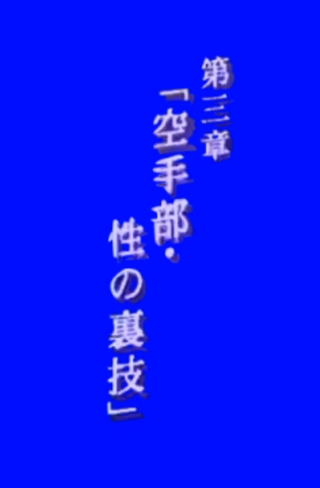
インタビュー テロップ フォント
インタビュー テロップ フォント. そしてこのフォントは 最初に全て決めておきましょう テロップを入れるたびにフォント何にしようかな〜と選ぶ時間がもったいないです 時間短縮のためにもフォントを決めておく事をオススメします 状況に応じたおすすめのフリーフォントを一部紹介し. 3 受注時に要確認 テロップは作業時間が数倍に 31 webではテロップが必須な時代;. 4 見やすいテロップとは 41 文字の色や輪郭は明度差を意識する;.
字幕とテロップはどう違うのですか。 テロップは一般的にはテレビ画面に映し出された文字のことを指しますが、当社では便宜上、字幕作成とテロップ作成を以下のように区別しています。 srtやvttファイル作成のみお願いできますか。 はい、可能です。. 3 受注時に要確認 テロップは作業時間が数倍に 31 webではテロップが必須な時代;. フォント使用例 「番組にテロップを入れる場合、フォントはvtr を編集する段階で選ぶことが多いのですが、『世界遺産』では番組内での統一感を大切に考えて、ひとつのフォントをメインで使うという方針を貫いています。.
目次 1 テロップの意味 11 ナイトスクープが最初に入れた?;. テロップ書体 書体見本 テロップ書体 活用例 デザイナーインタビュー qどのような書体がテロップに適していると思いますか? デザイナーa:私は映像編集者ではありませんが、テロップを使う意味や目的からイメージしながら回答させていただきます。.